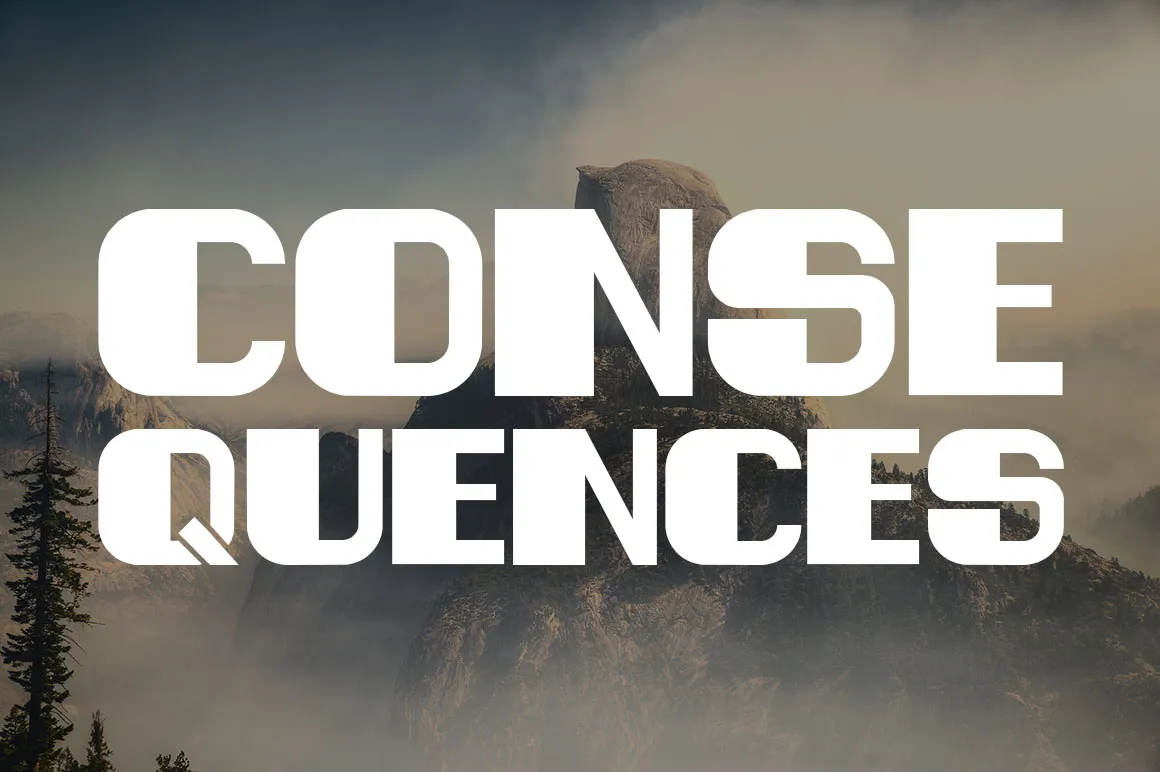
Estou aqui uma descrição envolvente para a página de download da font ‘Consequences Typeface’. Na categoria de fonts sans-serif, a Hamilton apresenta-nos Consequences Typeface, um design que surge com elegância e clareza, perfeito para qualquer projeto gráfico. Introduzido por Vladimir Nikolic, esta é uma fonte sans-serif icônica e limpa. Foi desenhada à mão utilizando-se de um tablet digital. O design perfeito para branding, logotipos, títulos em exposição, sinalização, flyers ou camisetas, headlines e mais. Consequences oferece o conjunto perfeito para quem procura uma fonte de estilo moderno e elegante que se destaca de forma simples, mas eficaz. Este é um excelente adorno para qualquer projeto gráfico, seja em impressão digital ou tradicional. Experimente Consequences agora e faça sua próxima produção estilosa e única!